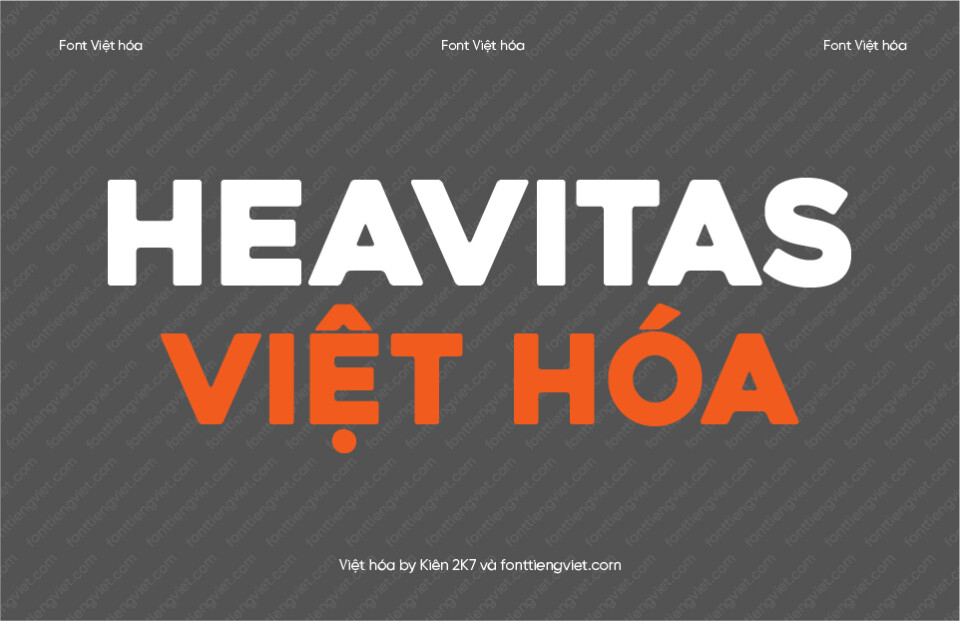
Font Việt hóa 1FTV Heavitas
Giới thiệu về bộ Font Việt hóa 1FTV Heavitas
Trong thế giới đồ họa hiện đại, việc lựa chọn một bộ Font Miễn Phí phù hợp đóng vai trò quyết định đến tính thẩm mỹ của sản phẩm. Font Việt hóa 1FTV Heavitas là một phiên bản nâng cấp hoàn hảo từ phông chữ Heavitas nguyên bản. Với các đường nét dày dặn, mạnh mẽ và dứt khoát, bộ font này đã được tối ưu hóa hoàn toàn bảng mã tiếng Việt, giúp người dùng không còn lo lắng về lỗi hiển thị dấu khi thiết kế các ấn phẩm truyền thông hay tài liệu học tập.
Đặc điểm nổi bật của Font Việt hóa 1FTV Heavitas
Đặc trưng lớn nhất của Font Việt hóa 1FTV Heavitas chính là phong cách không chân (Sans-serif) mang hơi hướng hiện đại và chuyên nghiệp. Các ký tự được thiết kế với độ tương phản thấp nhưng vẫn giữ được sự rõ ràng, dễ đọc ngay cả ở kích thước nhỏ. Điều này khiến nó trở thành lựa chọn ưu tiên cho các tiêu đề lớn, logo, hoặc bìa sách giáo khoa cần sự trang trọng và uy tín.
Ứng dụng Font Việt hóa 1FTV Heavitas trong giáo dục và thiết kế
Đối với các bạn học sinh và giáo viên, Font Việt hóa 1FTV Heavitas là công cụ đắc lực để tạo ra những bài thuyết trình PowerPoint sinh động. Sự chắc chắn trong từng nét chữ giúp nội dung bài giảng trở nên nổi bật và thu hút sự chú ý của người xem. Ngoài ra, các nhà thiết kế tự do thường sử dụng bộ font này cho các dự án xây dựng thương hiệu cá nhân hoặc làm poster sự kiện trường học vì tính linh hoạt cao.
Kết luận về bộ phông chữ 1FTV Heavitas